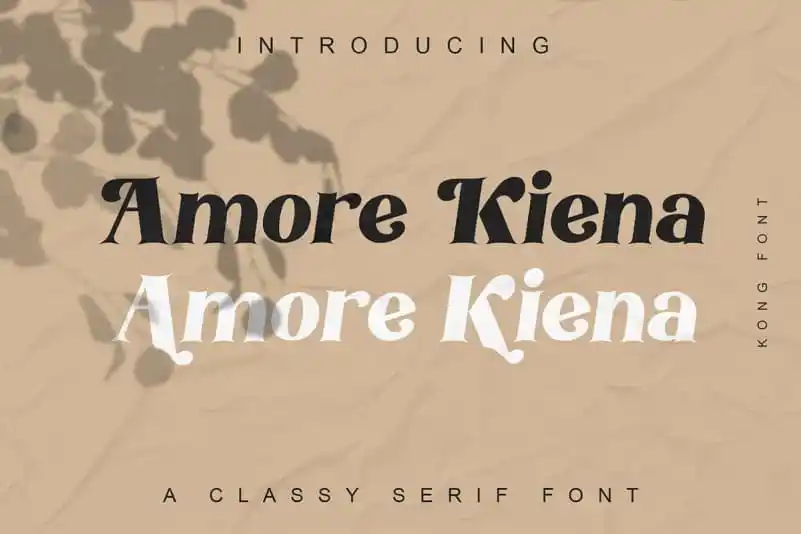
Descubra a inspiração clássica dos anúncios no Amore Kiena Serif Font, uma elegante fontesimaria criada ao estilo artesanal para personalizar seus projetos de design gráfico com facilidade. Inspirado nos ícones das grandes cidades e publicidade do passado, este fonte é um verdadeiro passeio pela história visual da arte tipográfica. Com seu design sofisticado e estilizado, o Amore Kiena proporciona uma experiência única para designers de logotipos, letras de porta-retratos, postais, roupas, etiquetas – em essência, qualquer projeto que exige uma fonte serif de qualidade. Este font traz mais do que apenas tipografia clássica; ele oferece alternativas de tipos abertamente, ligações comuns e até mesmo a opção de adicionar swashes para criar um design personalizado único. Seja para criar um logo memorável ou um poster impressionante, o Amore Kiena está equipado para transformar qualquer projeto em uma obra-prima visual. Sujeitivo à adaptação e adaptabilidade, este fonte é perfeito tanto para designers profissionais quanto para aqueles iniciantes que desejam explorar a arte da tipografia de maneira criativa e inspiradora. Se você busca um estilo sofisticado para seus projetos gráficos, onde a elegância e o poder do design combinam em uma união perfeita, o Amore Kiena Serif Font é definitivamente a escolha correta.